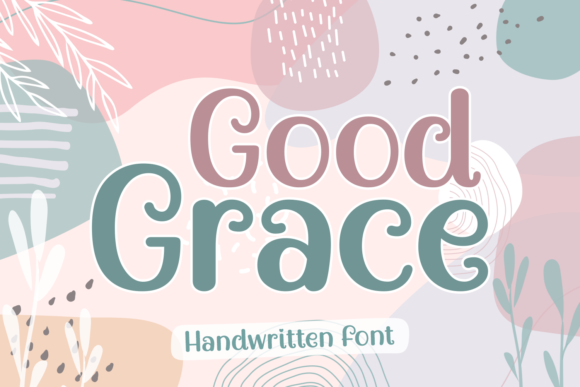
Good Grace Font
خط Good Grace – لمسة من الأناقة والتميز في تصاميمك
أضف لمسة من الفخامة والرقي إلى مشاريعك مع Good Grace Font، الخط العصري الذي يجمع بين الأناقة والوضوح في تصميمه الفريد. يتميز هذا الخط بانسيابية حروفه وتناسقها المثالي، مما يجعله خيارًا مثاليًا لمجموعة واسعة من الاستخدامات، بما في ذلك:
✅ تصميم الشعارات والهويات البصرية
✅ الدعوات وبطاقات التهنئة الفاخرة
✅ أغلفة الكتب والمجلات
✅ منشورات وسائل التواصل الاجتماعي
✅ المشاريع الإبداعية والمتاجر الرقمية